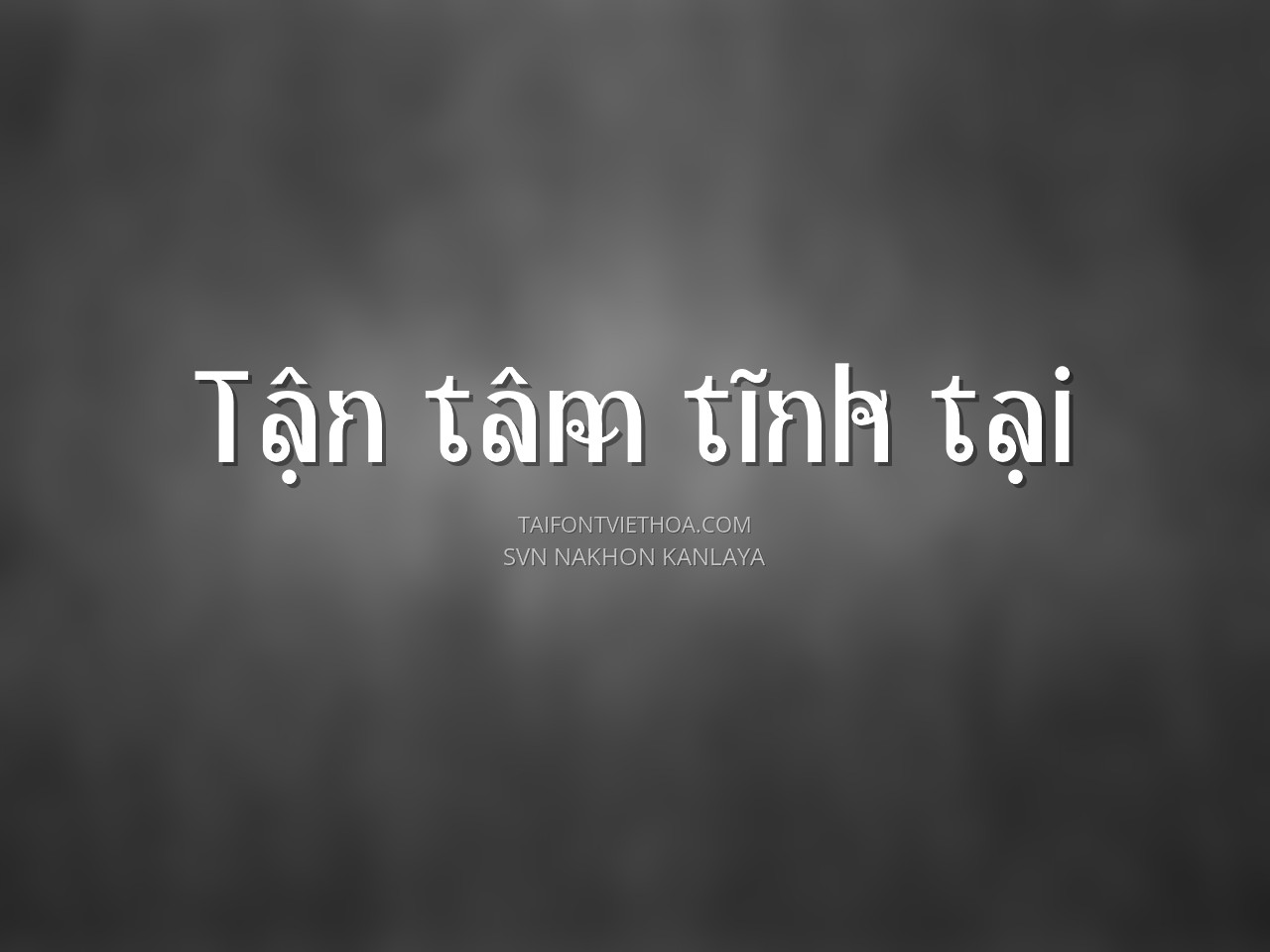
Font việt hóa SVN Nakhon Kanlaya
Tác giả Font: Ahmad Ramzi Fahruddin
Giới thiệu về font SVN Nakhon Kanlaya – Phong cách thư pháp Thái Lan độc đáo và uyển chuyển
SVN Nakhon Kanlaya là phiên bản Việt hóa của font Nakhon Kanlaya – một kiểu chữ thư pháp lấy cảm hứng từ nghệ thuật viết tay truyền thống Thái Lan. Font mang đậm nét văn hóa đặc trưng với các đường nét uyển chuyển, mềm mại và tinh tế, thể hiện sự hòa quyện giữa truyền thống và tính hiện đại trong thiết kế.
Phiên bản Việt hóa của SVN Nakhon Kanlaya được Taifontviethoa.comtuyển chọn kỹ lưỡng, hỗ trợ đầy đủ dấu tiếng Việt và hơn 50 ngôn ngữ khác. Font giữ nguyên tinh thần nghệ thuật của bản gốc, giúp các nhà thiết kế dễ dàng áp dụng trong các dự án văn hóa, nghệ thuật hoặc các thiết kế mang tính cá nhân hóa và sáng tạo.
Đặc trưng thư pháp uyển chuyển – Lý tưởng cho thiết kế nghệ thuật và văn hóa Đông Nam Á
SVN Nakhon Kanlaya có các nét bút thanh thoát, mềm mại với các đường cong uyển chuyển đặc trưng của thư pháp Thái Lan. Font tạo cảm giác truyền thống, thanh lịch và đầy cảm xúc, phù hợp cho các dự án thiết kế tranh thư pháp, bìa sách nghệ thuật, logo thương hiệu truyền thống và các sản phẩm sáng tạo mang hơi hướng văn hóa Đông Nam Á.
Ứng dụng lý tưởng: thiết kế tranh thư pháp, bìa sách nghệ thuật, thiệp mời, poster sự kiện văn hóa, sản phẩm thủ công và các dự án sáng tạo mang phong cách truyền thống và bản sắc văn hóa. Ngành nghề phù hợp: nghệ thuật, văn hóa, giáo dục, truyền thông, thiết kế nội thất phong cách Đông Nam Á và các thương hiệu định vị theo tinh thần truyền thống.